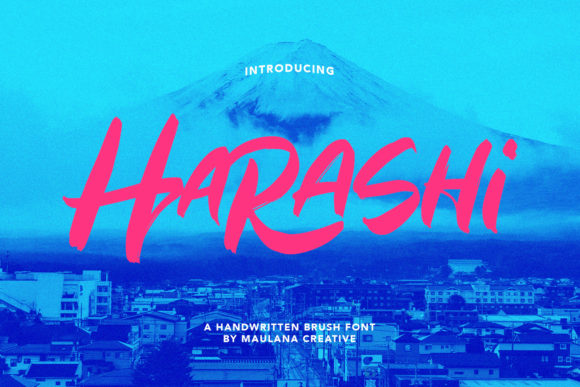
Creativefabrica Harashi Font
[Creativefabrica] Harashi Font
Хараши - это крутой, урбанистический и аккуратный шрифт, написанный от руки кистью.
Он отличается плавными изгибами и идеально подходит для модного брендинга или редакционного дизайна.
Добавьте его уверенно в свои проекты, и вам понравится результат.